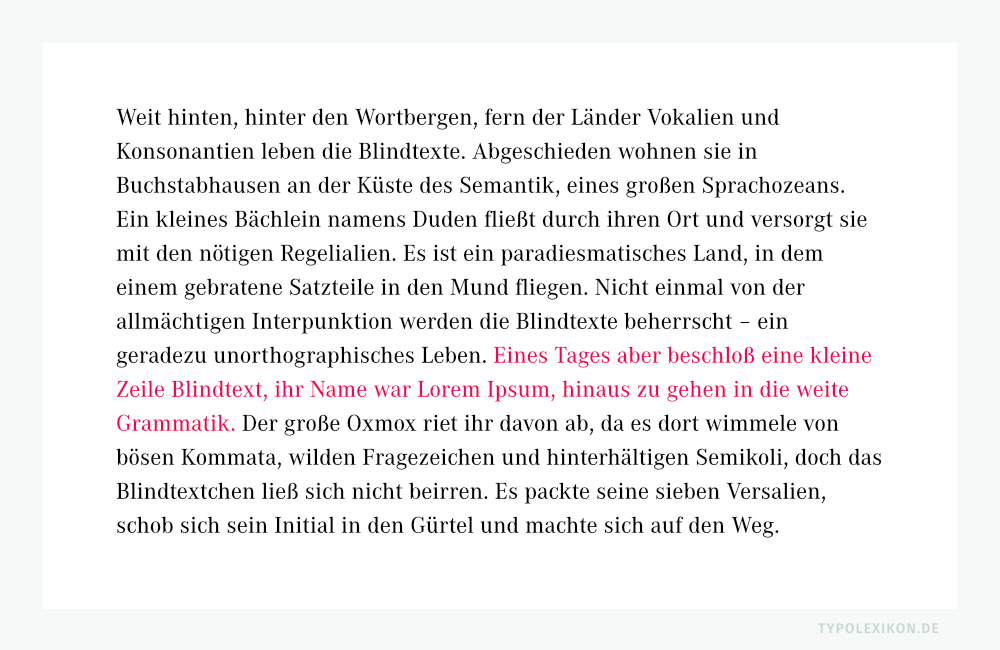
Farbauszeichnung einer Schrift
Farbauszeichnung ist eine farbliche Hervorhebung eines Buchstabens, Sonderzeichens, einer Indo-Arabischen Ziffer, eines Wortes oder einer Textpassage im »Glatten Satz« oder »Gemischten Satz«, also innerhalb eines fortlaufenden Textes. Farbauszeichnungen sind eine Methode der Schriftauszeichnung.